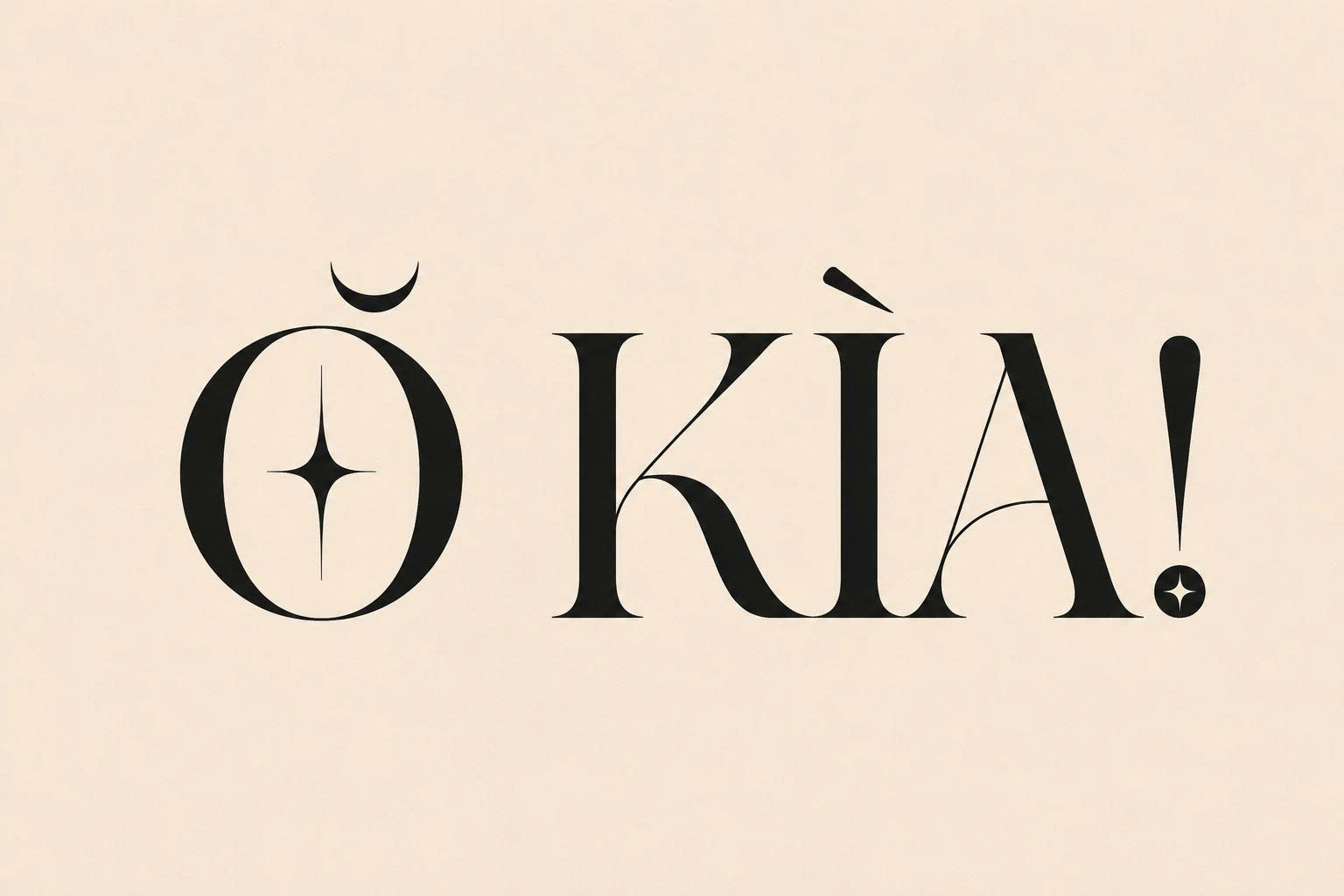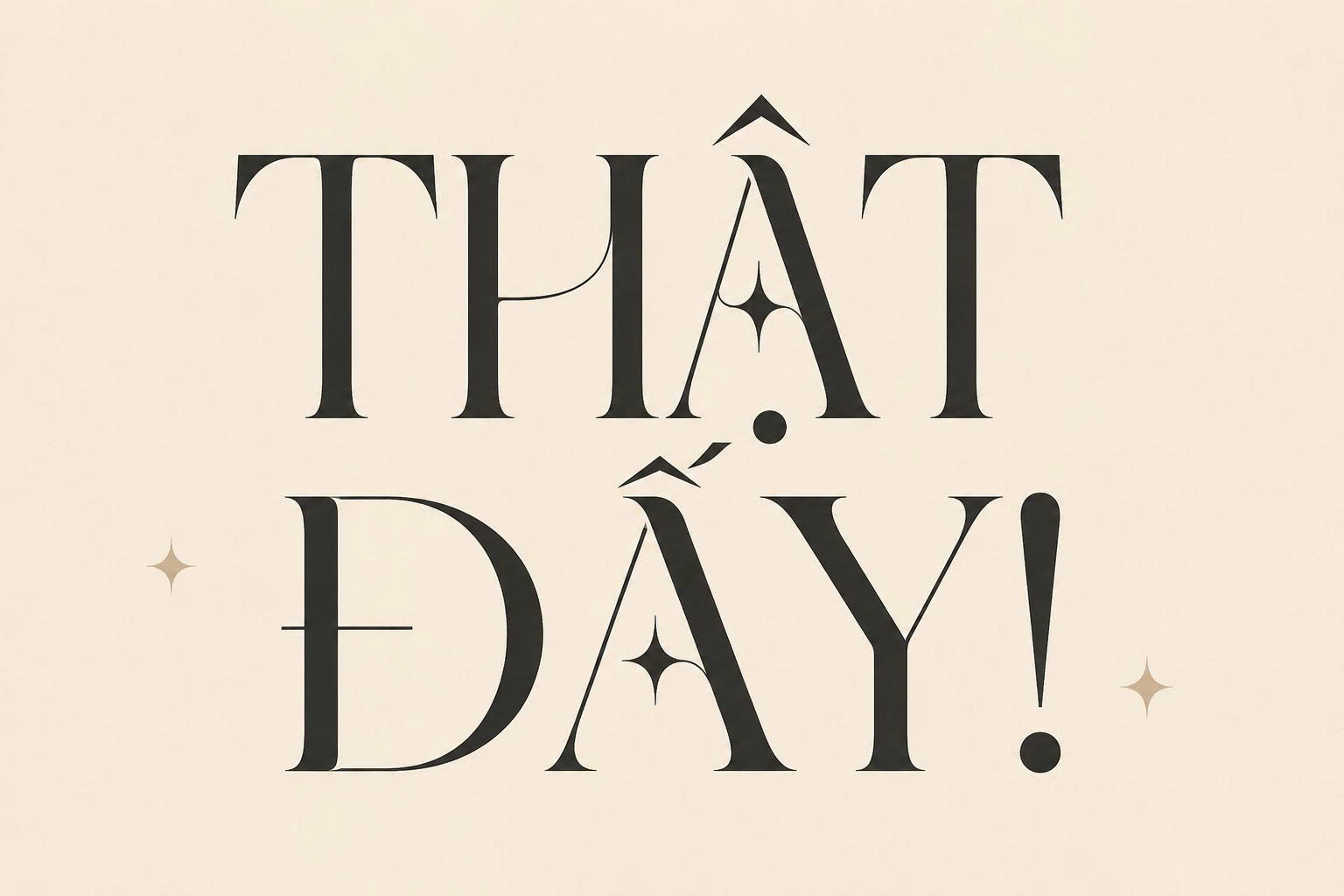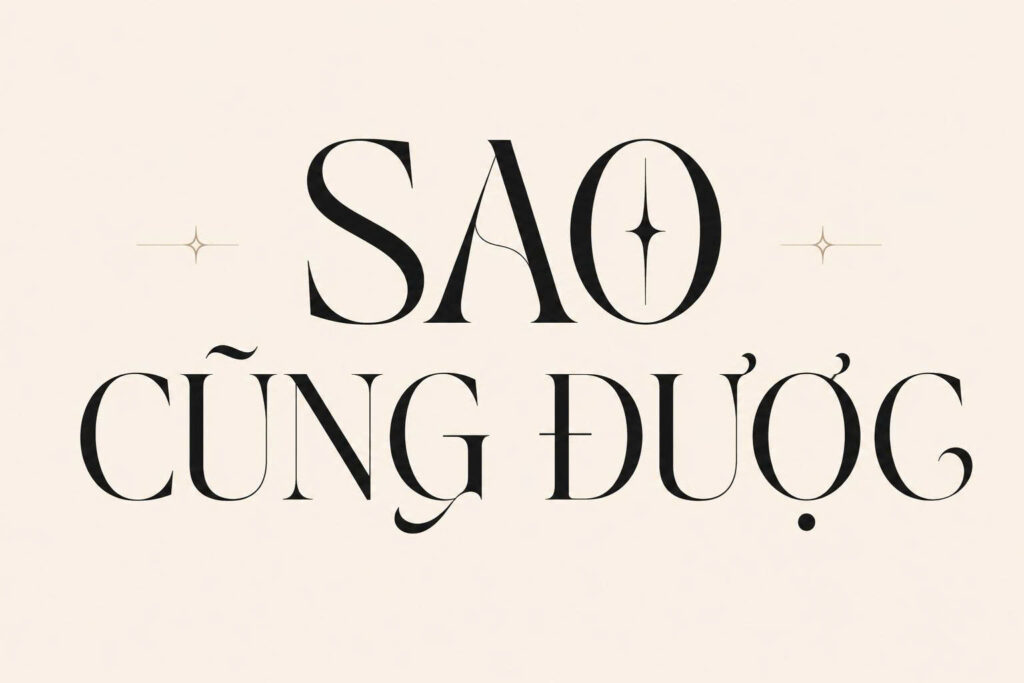
Font Việt hóa Boxroom là bộ phông chữ thuộc dòng Modern Serif đương đại lấy cảm hứng từ cấu trúc phân chia các phòng chức năng nhỏ gọn và nghệ thuật bài trí nội thất tối giản. Nổi tiếng với tỷ lệ khung chữ thu hẹp thanh lịch, các góc chân chữ sắc sảo và đường cong tinh tế, font Việt hóa Boxroom kiểu Serif hiện đại là chất liệu trực quan tuyệt vời để các kiến trúc sư, nhà thiết kế kiến tạo chiều sâu tri thức cho các bản vẽ phối cảnh căn hộ studio, homestay nhà nhỏ hay các ấn phẩm tạp chí kiến trúc nội thất.
Tỷ lệ khung chữ ngăn nắp và vẻ đẹp tri thức của font Việt hóa Boxroom
Điểm cuốn hút của font Việt hóa Boxroom nằm ở cấu trúc hình thể hẹp ngang nhưng sở hữu chiều cao ký tự (x-height) lớn, giúp các khối chữ khi xếp cạnh nhau tạo nên nhịp điệu ngăn nắp như những ngăn tủ sách được đóng đo chuẩn xác. Khác với các dòng Serif truyền thống nặng nề, Boxroom mang lại cảm giác thoáng đãng, ấm cúng và đượm chất học thuật tinh tế.
Sự ổn định về mặt thị giác của dòng font này tạo nên cảm giác tin cậy, sự ngăn nắp và tư duy tối ưu hóa không gian của đơn vị chủ trì đồ án. Khi kết hợp cùng các vật liệu kiến trúc nội thất đương đại như gỗ sồi sáng màu, khung kim loại đen mảnh, vải nỉ màu be hay gạch thẻ ốp tường trong các căn nhà lắp ghép thông minh, Boxroom tạo nên sự hòa quyện thẩm mỹ vô cùng trang nhã.
Tư vấn từ chuyên viên: SLTF Boxroom sở hữu cấu trúc chân chữ hiện đại và thân chữ thanh mảnh. Để bản thiết kế đạt hiệu quả thẩm mỹ tốt, bạn nên sử dụng phông chữ này cho các tiêu đề chính, tên dự án hoặc câu khẩu hiệu ngắn ở kích thước lớn từ 18pt trở lên.
03 Ứng dụng SLTF Boxroom vào công trình thực tế
Nhờ vẻ ngoài tri thức và tính thẩm mỹ cao cấp, bộ phông chữ này mang lại giá trị thực tế lớn trong khâu hoàn thiện các công trình hiện đại:
- Hệ thống biển tên phòng và Bảng phân khu Homestay Tối giản: Những nét chữ thanh mảnh của SLTF Boxroom rất ăn ý khi gia công chữ nổi bằng inox đen mờ hoặc khắc chìm trên gỗ tự nhiên, giúp các căn phòng trong khu nhà lắp ghép toát lên phong thái tao nhã và ngăn nắp.
- Bìa hồ sơ giải pháp nhà ở nhỏ gọn: Sử dụng font Việt hóa Boxroom cho tên dự án và tiêu đề các chương mục giúp tập hồ sơ toát lên vẻ ngoài của một ấn phẩm kiến trúc danh giá, tạo niềm tin lớn với các chủ đầu tư yêu chuộng lối sống tinh gọn.
- Trang trí không gian góc đọc sách và Góc làm việc gác lửng: Phông chữ này khi in trên kính mờ hoặc kim loại sơn tĩnh điện sẽ giúp không gian làm việc toát lên chất nghệ thuật thanh lịch, khơi gợi cảm hứng tập trung sáng tạo.
03 Lưu ý bố cục font Việt hóa Boxroom kiểu Serif hiện đại luôn thanh lịch
Để khai thác hiệu quả vẻ đẹp của dòng font Serif hiện đại này mà không gây cảm giác chật chội cho bản vẽ, người thiết kế nên lưu tâm một số kinh nghiệm sau:
- Nới rộng nhẹ khoảng cách ký tự: Do cấu trúc chữ có chiều ngang hơi hẹp, bạn nên kéo giãn nhẹ khoảng cách giữa các con chữ khi viết hoa toàn bộ để câu chữ thông thoáng, giúp bố cục toát lên vẻ sang trọng và dễ nhận diện hơn.
- Cân đối khoảng cách dòng: Với cấu trúc ký tự có tỷ lệ thanh thoát, bạn nên thiết lập khoảng cách dòng ở mức vừa vặn (khoảng 1.3 – 1.4 lần cỡ chữ) để các dòng văn bản giữ được sự liên kết nhịp nhàng, tránh cảm giác chữ bị dàn trải quá mức.
- Bố trí nền màu đơn sắc tinh tế: Boxroom phát huy hiệu quả thị giác cao khi phối cùng các tông màu mang sắc thái đương đại như xám ấm, trắng kem, nâu đất nhạt hoặc đen tuyền trên nền vật liệu phẳng mờ, làm nổi bật đường nét sắc sảo của bộ chữ.